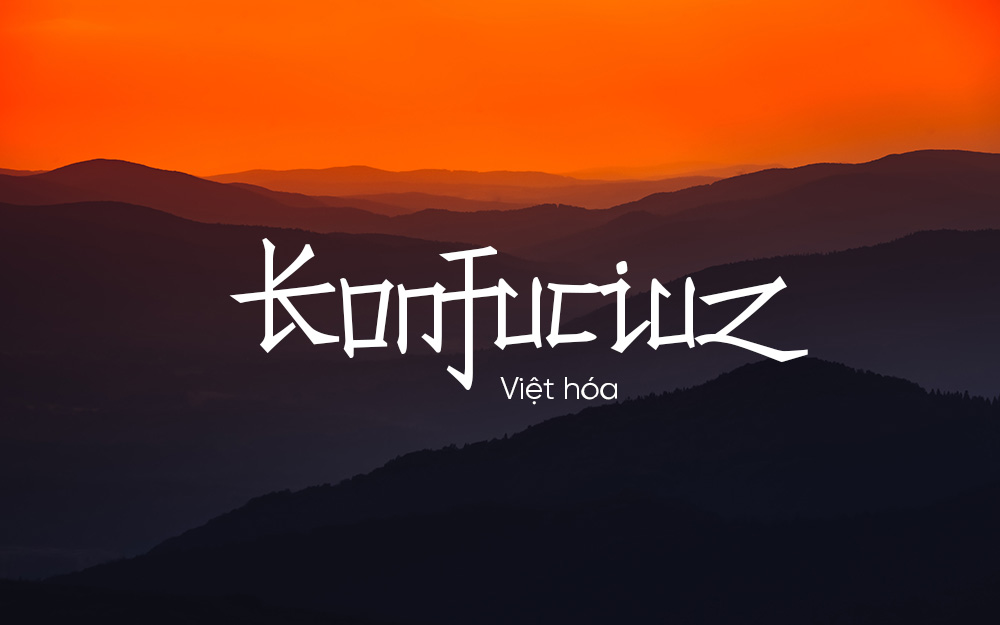
Font SVN Konfuciuz Việt Hóa
Font SVN Konfuciuz là một font chữ thuộc bộ font SVN độc đáo mang phong cách cổ điển Á Đông, tạo ấn tượng mạnh mẽ với các nét chữ mềm mại và cách điệu đầy nghệ thuật. Với sự kết hợp giữa truyền thống và hiện đại, font SVN Konfuciuz thường được sử dụng trong các thiết kế đậm chất văn hóa, từ bao bì sản phẩm, thương hiệu đến các ấn phẩm trang trí mang tính thẩm mỹ cao. Font chữ này không chỉ giúp làm nổi bật tính sáng tạo mà còn mang lại sự trang trọng, uy nghiêm, rất phù hợp cho các dự án liên quan đến văn hóa và nghệ thuật.